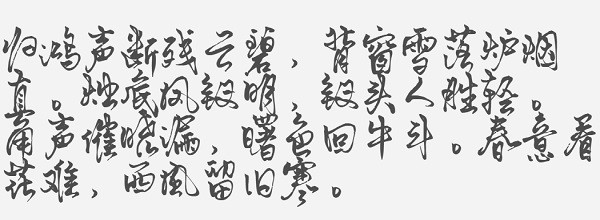
默陌風(fēng)雨欣游體ttf是非常好看的一種字體,字體整體非常的具有藝術(shù)氣息,非常的優(yōu)雅大方,不同于工工整整的字體,此字體略帶一種活潑奔放的感覺,可以廣泛應(yīng)用于廣告印刷等行業(yè),歡迎大家下載使用!
能夠適用于廣告設(shè)計(jì)、名片設(shè)計(jì)、包裝印刷、產(chǎn)品設(shè)計(jì)等應(yīng)用
默陌風(fēng)雨欣游體字形端正大方
非常適合廣告設(shè)計(jì)、平面設(shè)計(jì)、印刷包裝、正文標(biāo)題等人員使用
整體效果十分出眾
應(yīng)用領(lǐng)域:文字排版、美工設(shè)計(jì)、海報(bào)設(shè)計(jì)、書籍印刷、報(bào)紙周刊、平面設(shè)計(jì)等方面